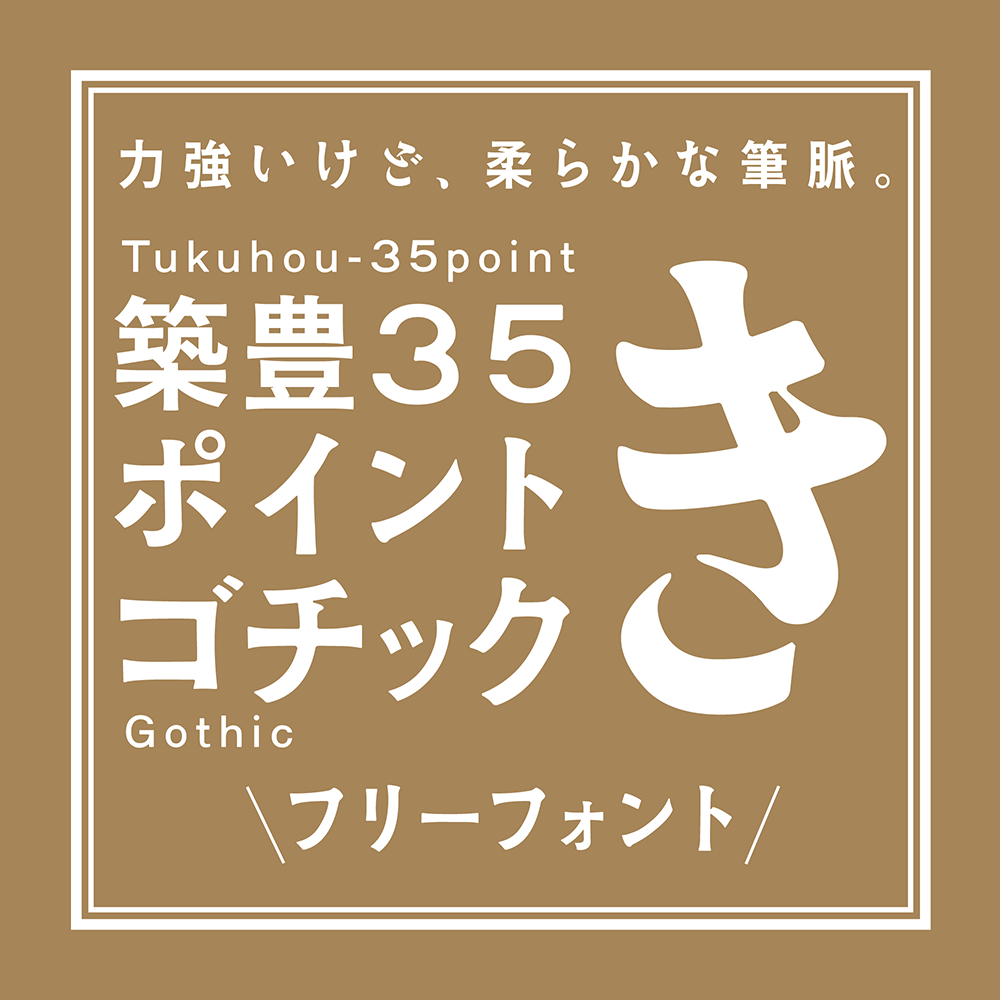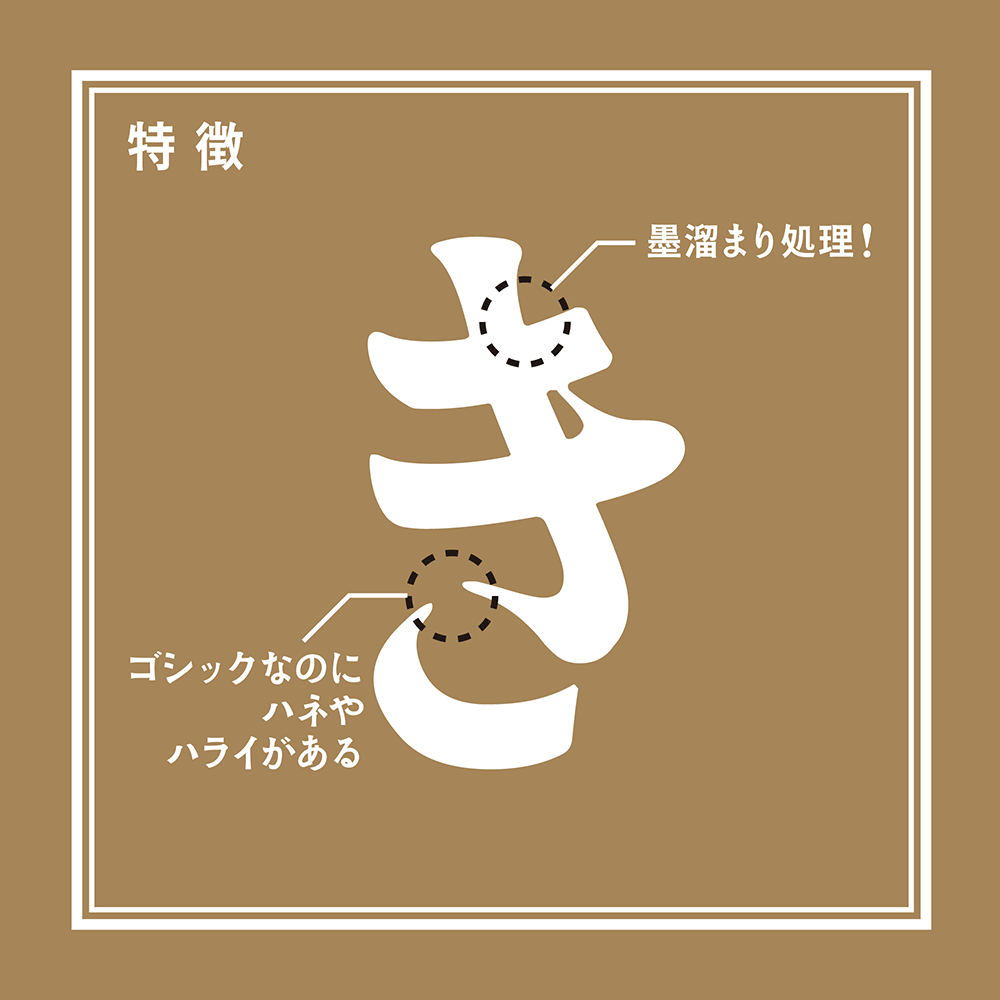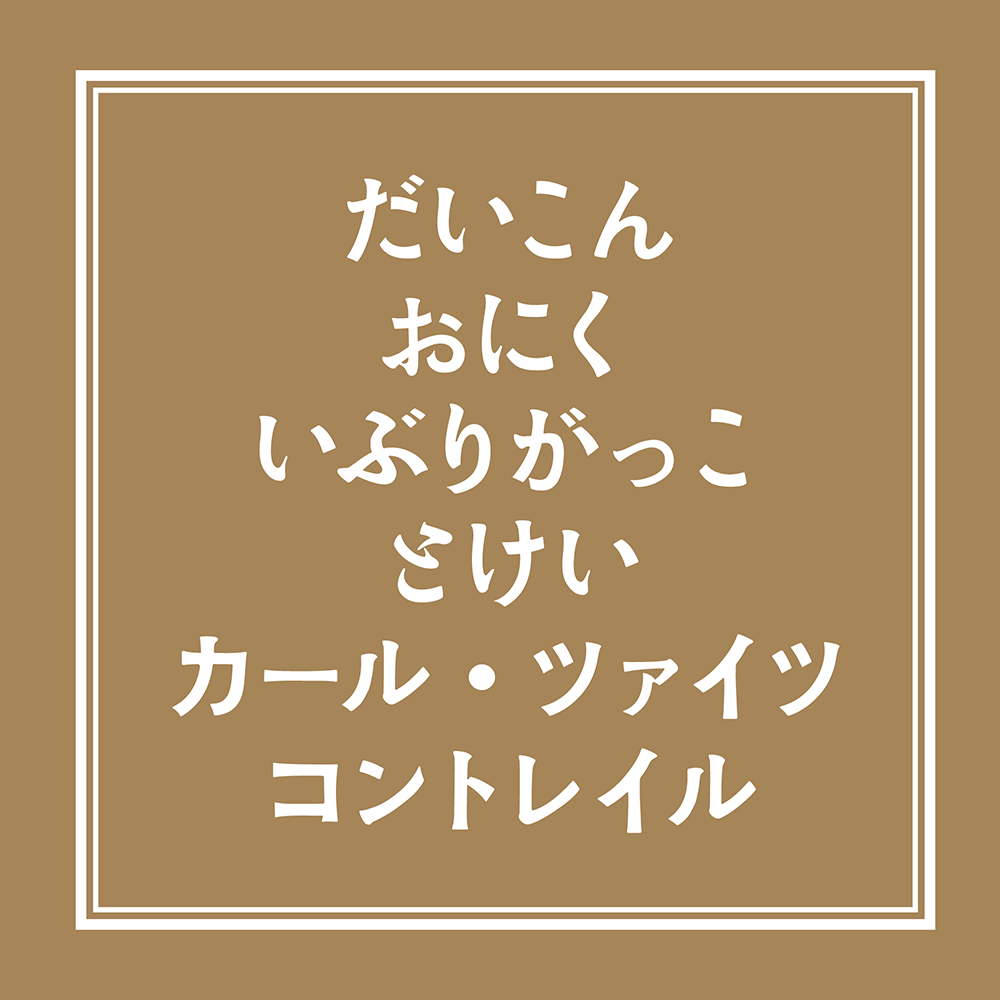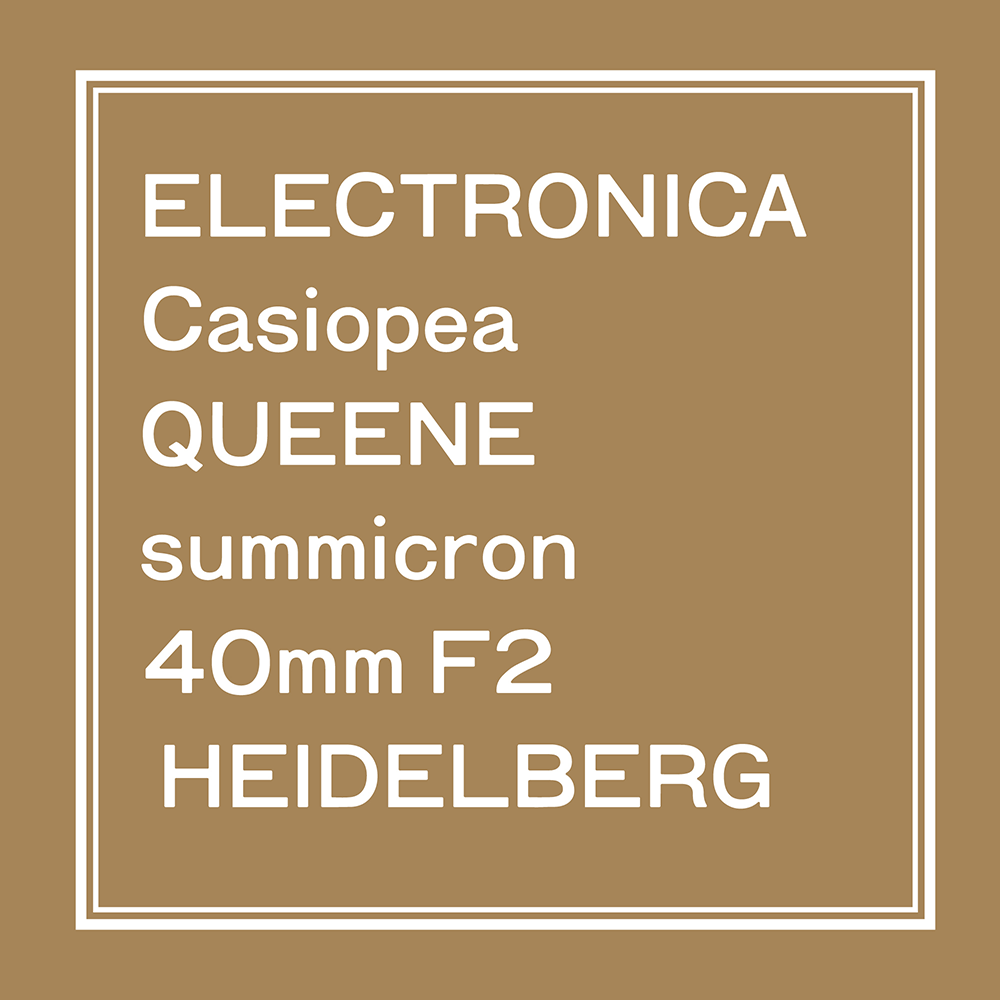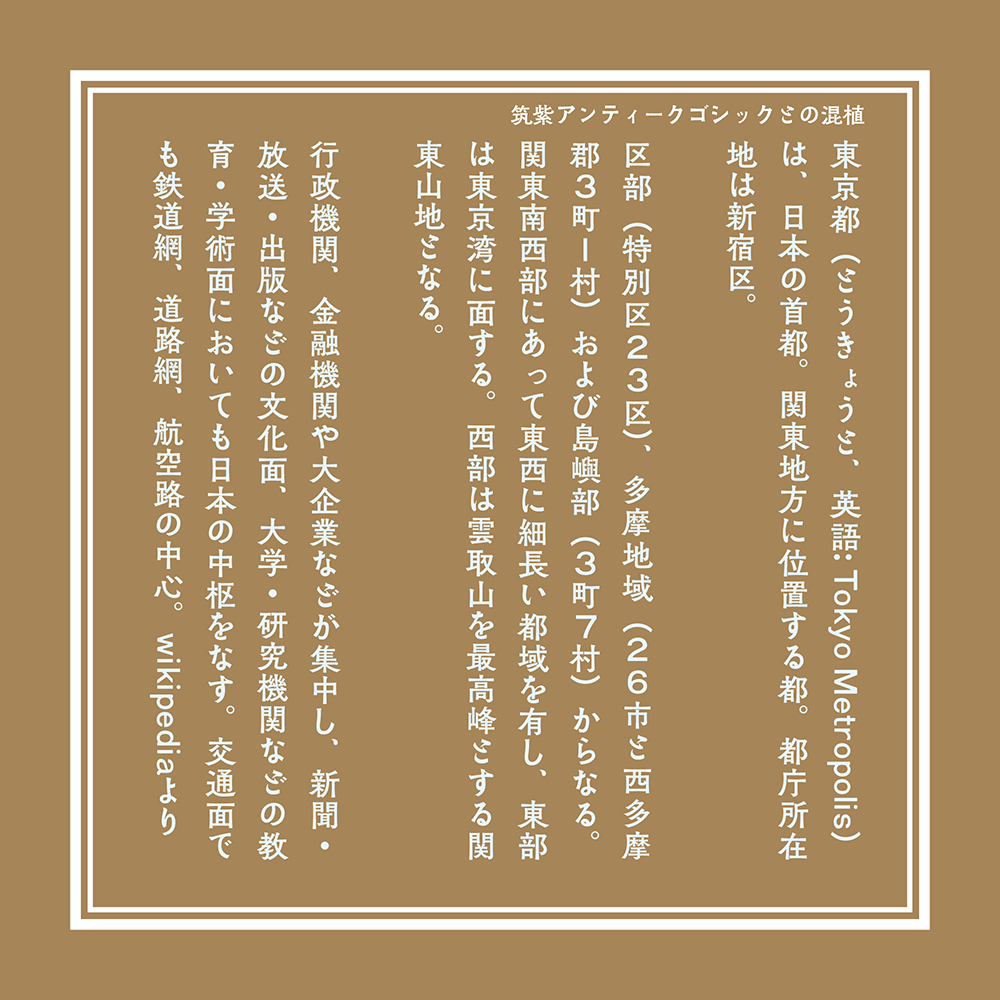
筑丰35点黑体(築豊35ポイントゴチック)以虚构的活字字体 “筑地35号黑体(築地35ポイントゴチック)” 为主题设计。假名骨架参考了民友社三十五号明朝体(筑地三十六号系列),是一款前所未见的复古风格黑体,尽可能保留了原字饱满的笔触与运笔力道。西文字体则基于照相排版时代常见的独特平衡感设计(请意会)。整体略微保留了墨水晕染的质感。
除假名、部分符号及西文字母外,其余字符均采用思源黑体的衍生字体「源石黑体」。特此向思源黑体与源石黑体的原创字体开发者致以深切谢意。
このフォントは架空の活字書体「築地35ポイントゴチック」があったらをテーマにしています。かな骨格は民友社三十五ポイント明朝(築地の三十六ポイント系)を参考にしています。今までありそうでなかったオールド系ゴシックで、元の豊かな筆脈と筆勢をなるべく残すようにしています。欧文は写植のときによく見たバランスが独特なやつが元です(伝われ)。全体的に軽く墨溜まりかけてあります。
かなと一部約物、アルファベットを除き源ノ角ゴシックの派生フォント「源石ゴシック」から利用しています。源ノ角ゴシックと源石ゴシックのオリジナルのフォントに深く感謝いたします。